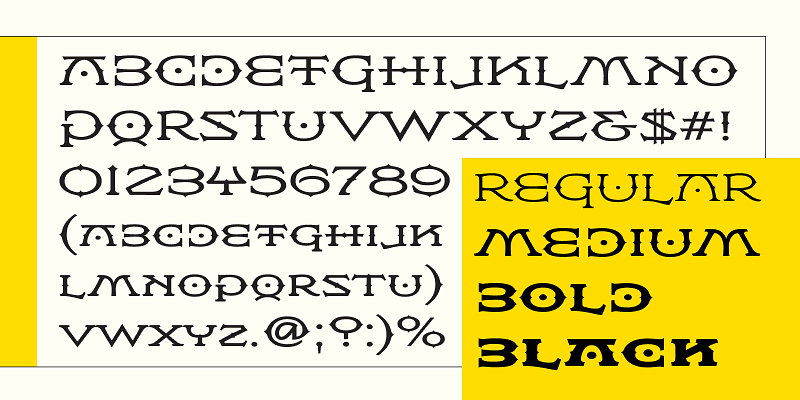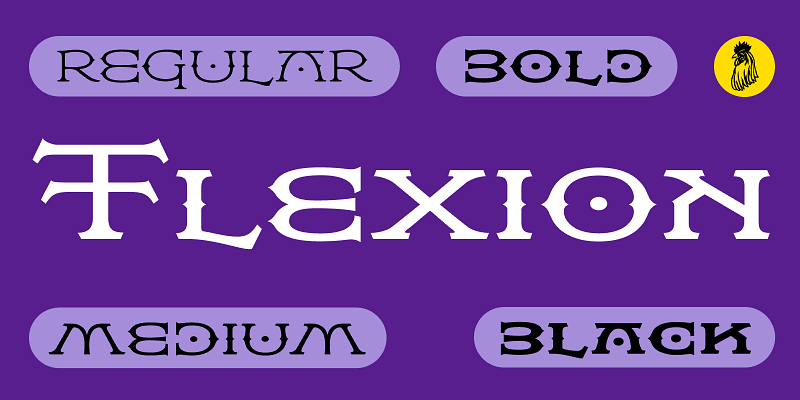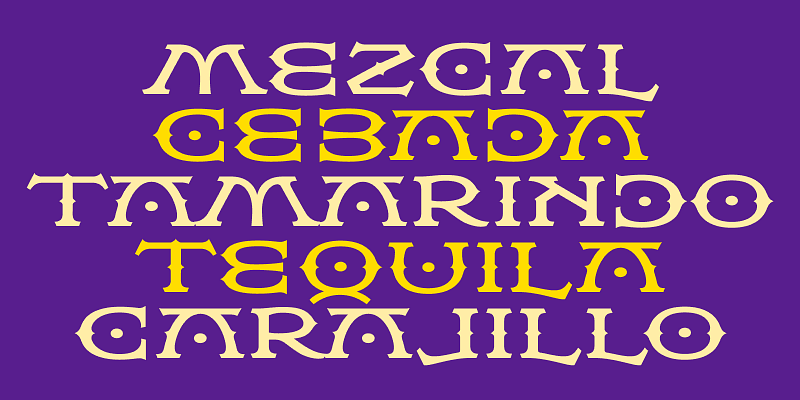
Flexion est une famille de polices décoratives. Conçue par Hal Taylor et John Langdon, elle est produite par Steve Jackaman et Ashley Muir. Alors qu’il travaillait sur l’adaptation cinématographique du film « Anges et Démons », Dan Brown a proposé à Langdon de créer un générique basé sur des ambigrammes. Le film s’est avéré trop long, mais Langdon a décidé de la commercialiser plutôt que de mettre la famille au placard. Flexion rappelle les fers à marquer et pourrait facilement servir à créer des identités fortes et imaginatives.